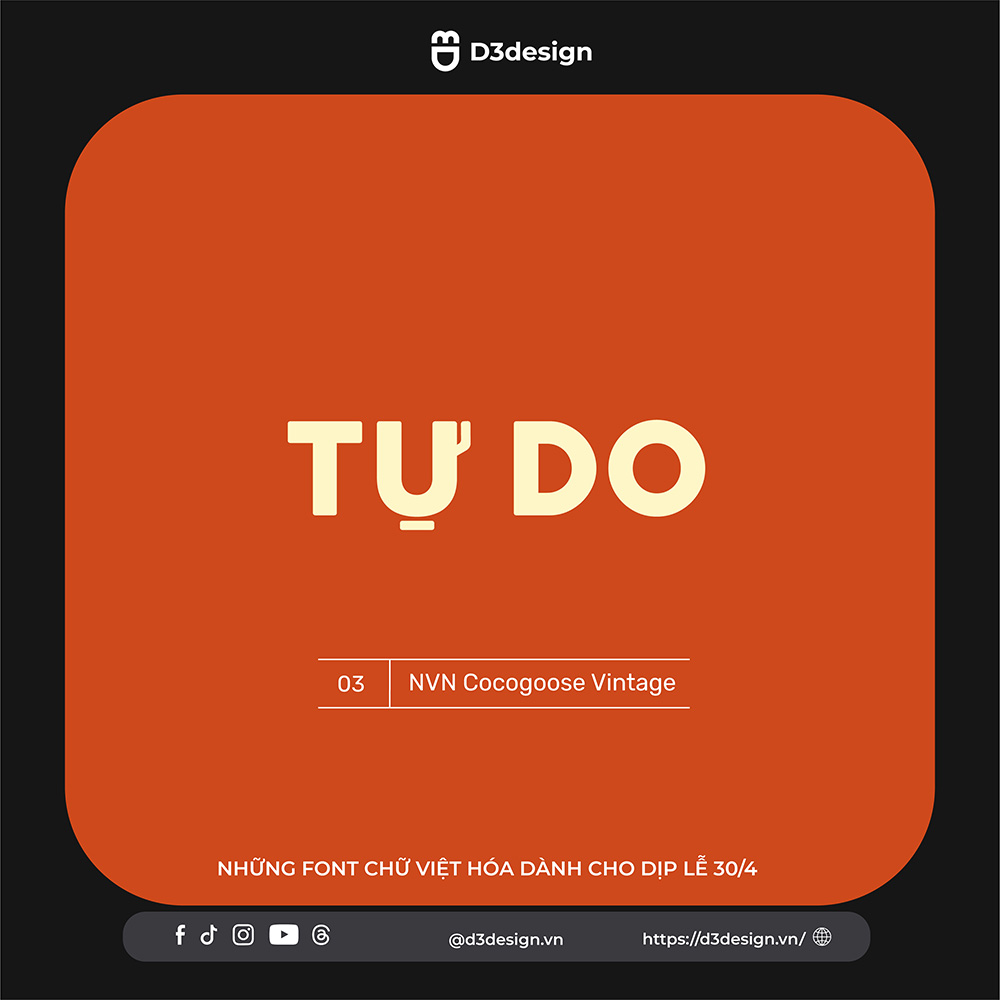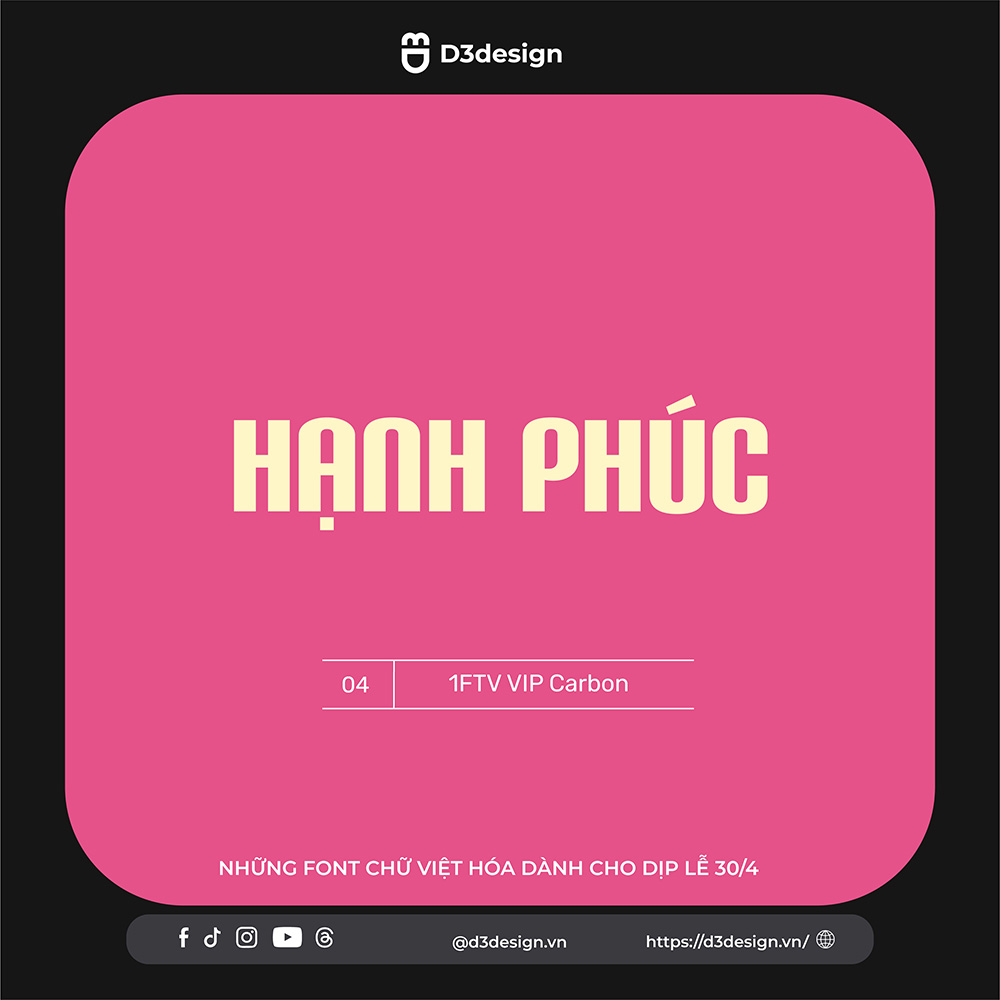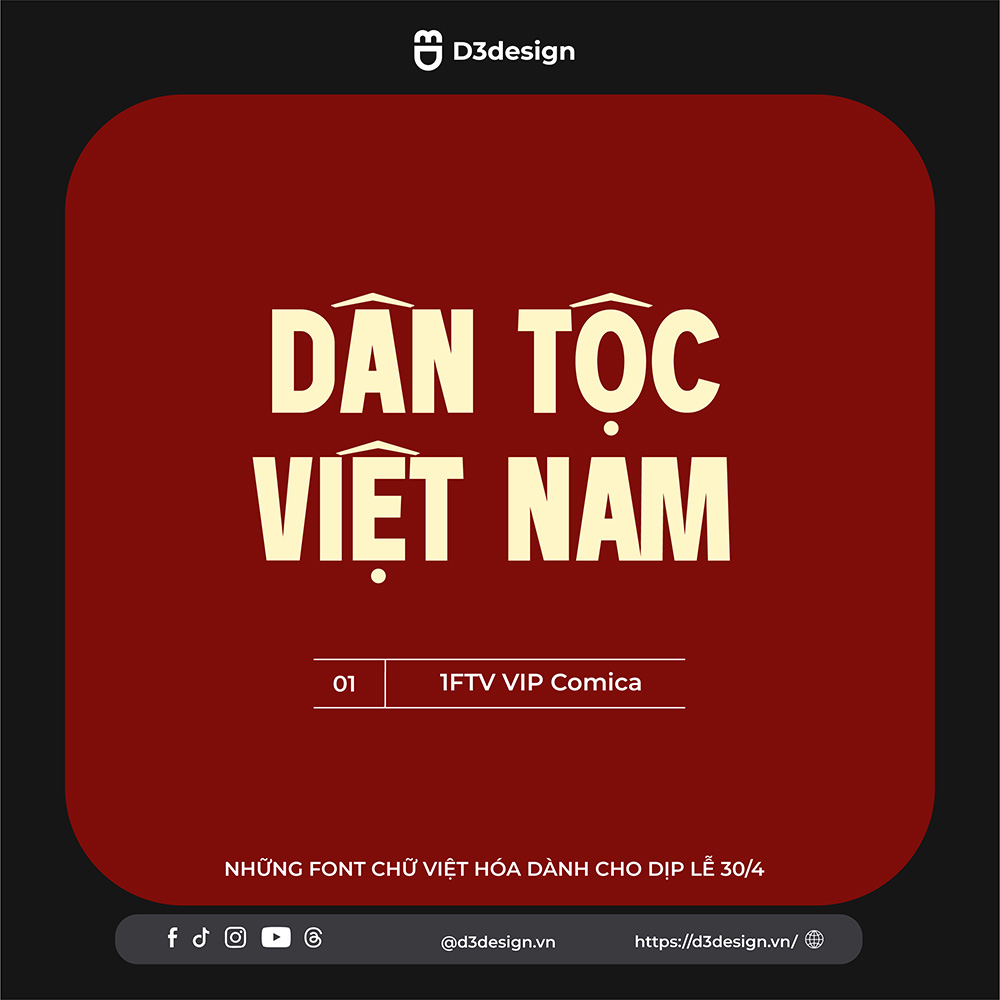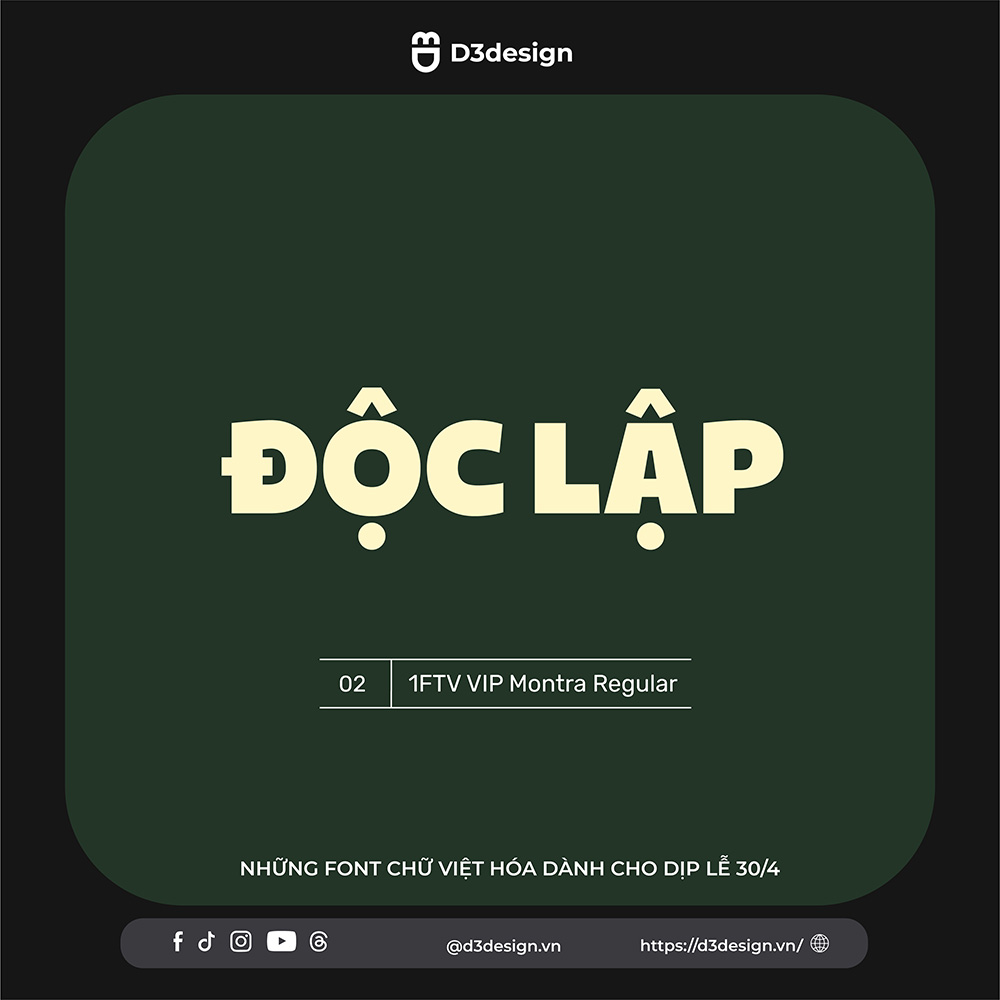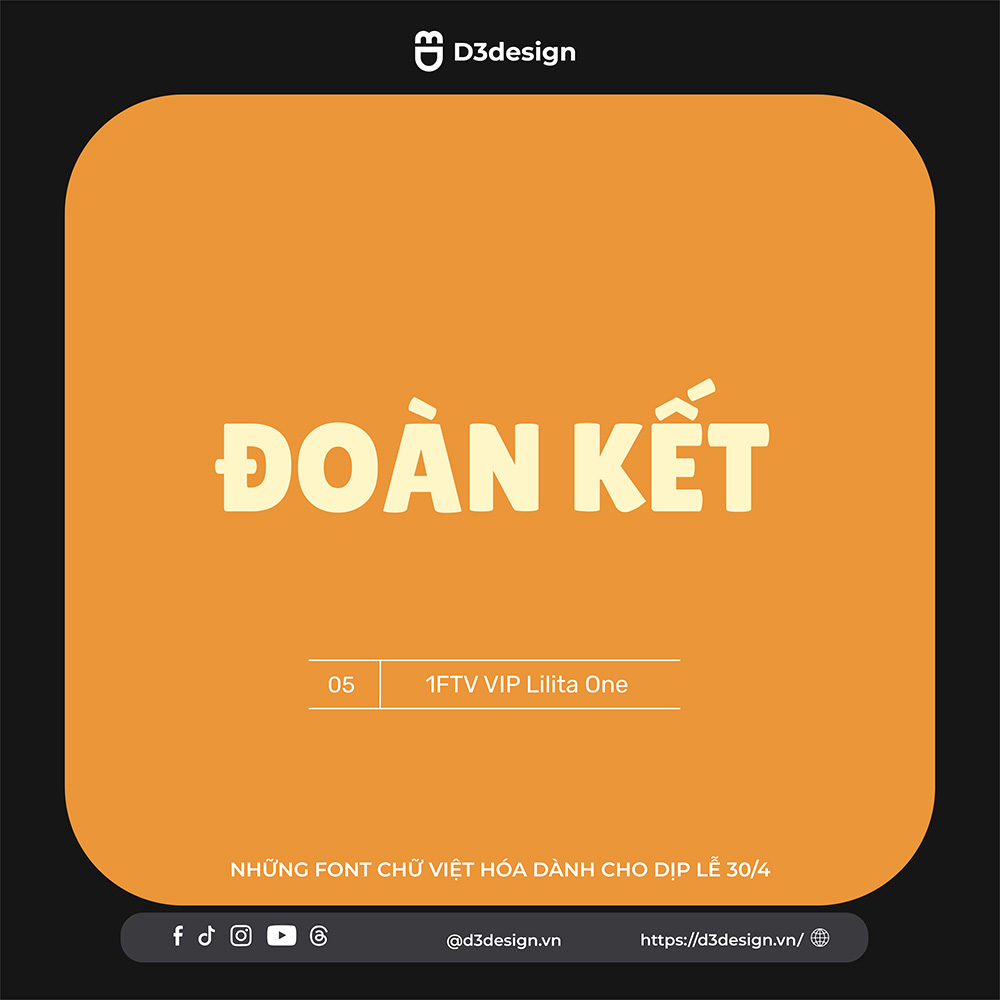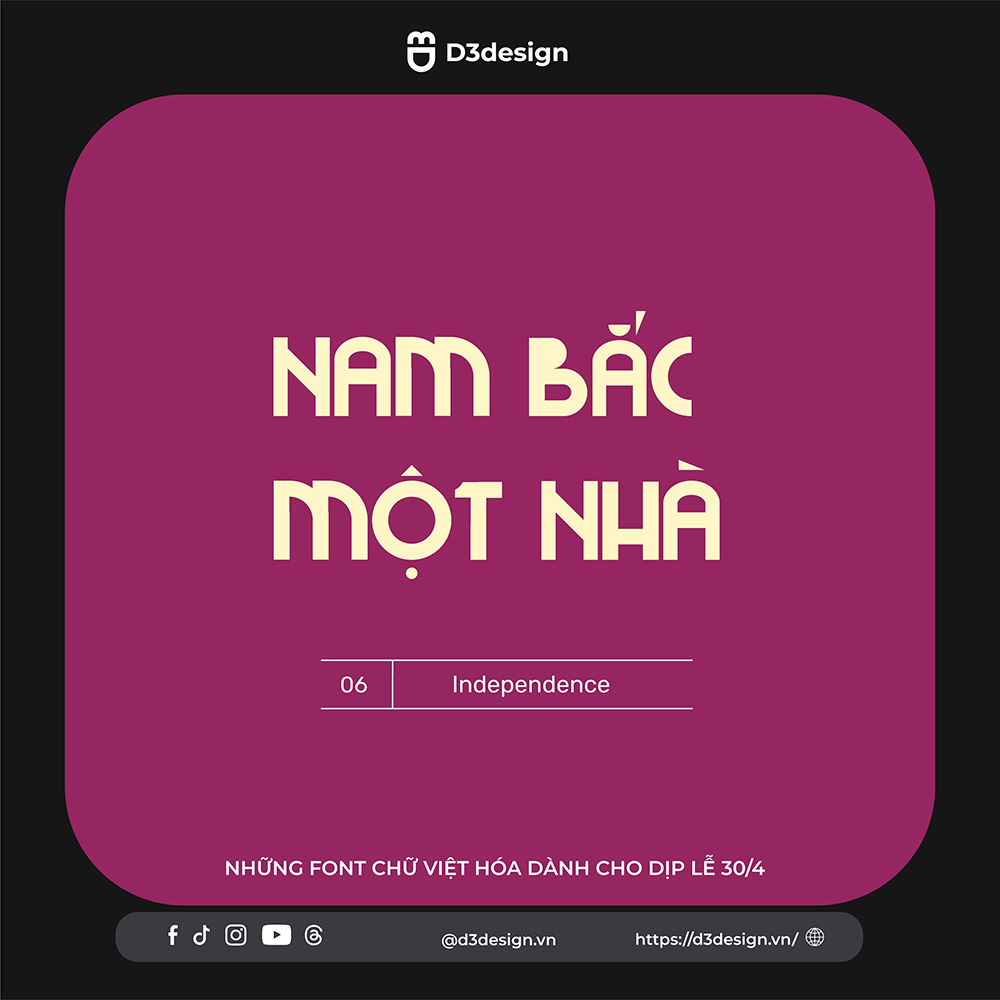
Tổng Hợp Những Font Việt Hóa Dành Cho Dịp Lễ 30/4
Ngày 30/4 – Ngày Giải phóng miền Nam, thống nhất đất nước – là một trong những cột mốc lịch sử quan trọng nhất của dân tộc Việt Nam. Vào mỗi dịp này, các ấn phẩm truyền thông, thiết kế banner, poster, thiệp chúc mừng hay bài viết tri ân luôn được đầu tư kỹ lưỡng về nội dung lẫn hình thức. Một trong những yếu tố không thể thiếu để làm nổi bật tinh thần hào hùng và không khí kỷ niệm đó chính là font chữ – đặc biệt là những kiểu chữ mang phong cách cổ động, truyền thống và đậm chất lịch sử.
Các ấn phẩm thiết kế cho ngày 30/4 thường mang thông điệp mạnh mẽ, thiêng liêng, thể hiện tinh thần dân tộc và lòng tự hào. Việc sử dụng font chữ phù hợp không chỉ giúp truyền tải cảm xúc tốt hơn mà còn giúp thiết kế trở nên chuyên nghiệp và ấn tượng hơn.
Những font chữ mang phong cách cổ điển, mô phỏng nét chữ trên các áp phích cổ động, biển hiệu thời kháng chiến sẽ làm tăng giá trị lịch sử cho thiết kế. Đồng thời, việc sử dụng đúng font chữ cũng góp phần tạo nên sự đồng nhất trong các chiến dịch truyền thông nhân dịp lễ lớn.
Tổng Hợp Những Font Việt Hóa Dành Cho Dịp Lễ 30/4
Font chữ là yếu tố không thể thiếu để tạo nên những thiết kế ý nghĩa nhân dịp kỷ niệm ngày Giải phóng miền Nam 30/4. Việc lựa chọn đúng font không chỉ giúp tôn vinh tinh thần dân tộc mà còn thể hiện sự tôn trọng với giá trị lịch sử. Hãy lựa chọn và sử dụng font một cách thông minh để mỗi ấn phẩm đều là một dấu ấn ghi nhớ ngày trọng đại của dân tộc.